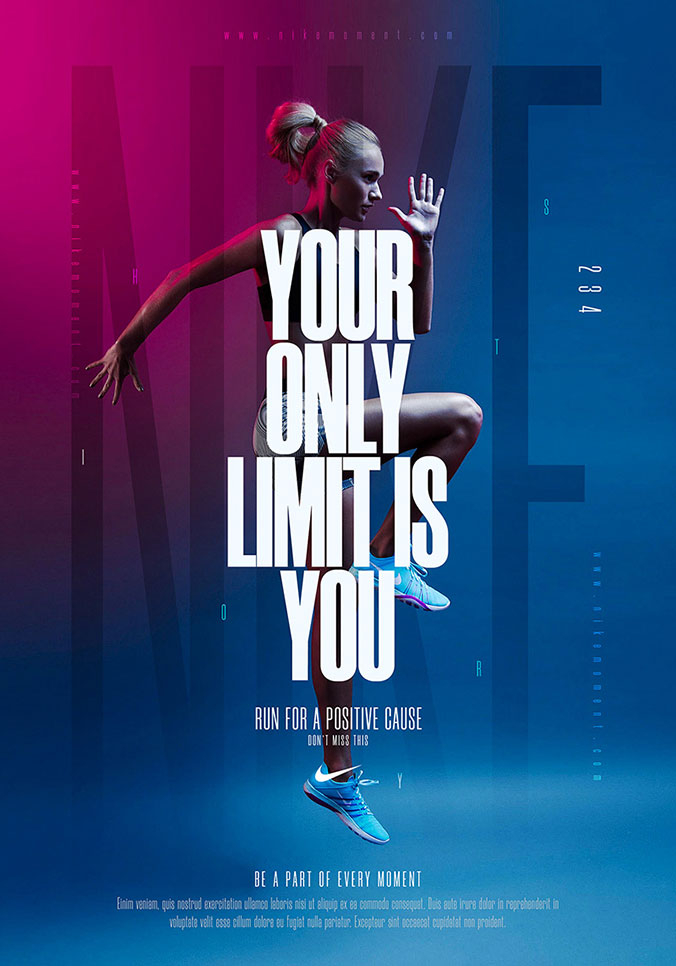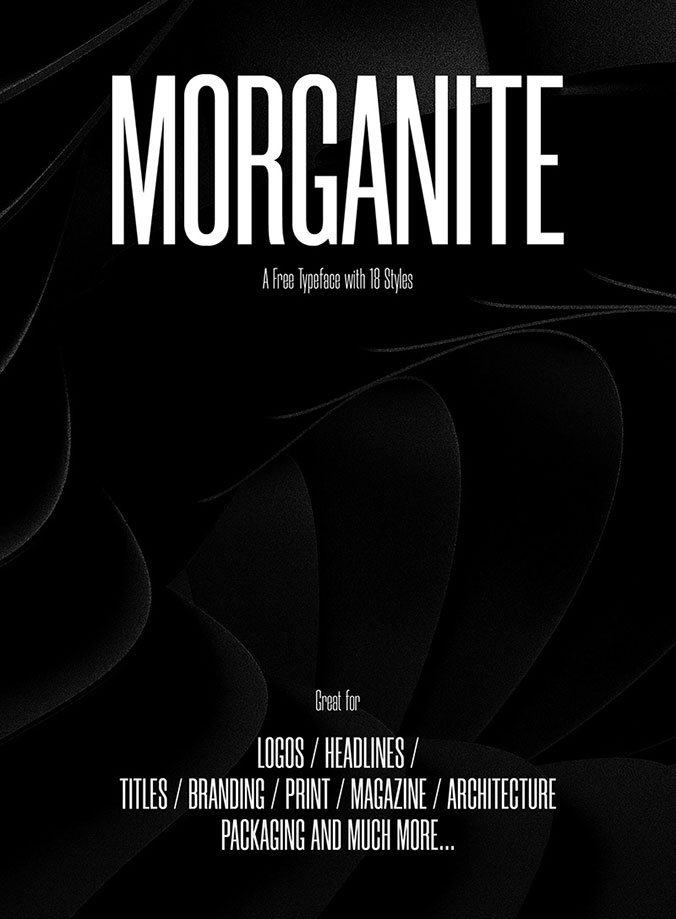
Morganite字體由印度新德里的設計師Rajesh Rajput所設計,可以免費用於個人和商業項目。但是未經書面許可,不得修改字體文件,用於二次發售,這也是對設計師的尊重,字體包括18種風格,從細到粗,還有傾斜體,字體風格非常優美,非常適合用在時尚、高端類型的海報設計作品。
Morganite字體包括18種風格,從細到粗,還有傾斜體,字體風格非常優美,非常適合用在時尚、高端類型的海報設計作品。